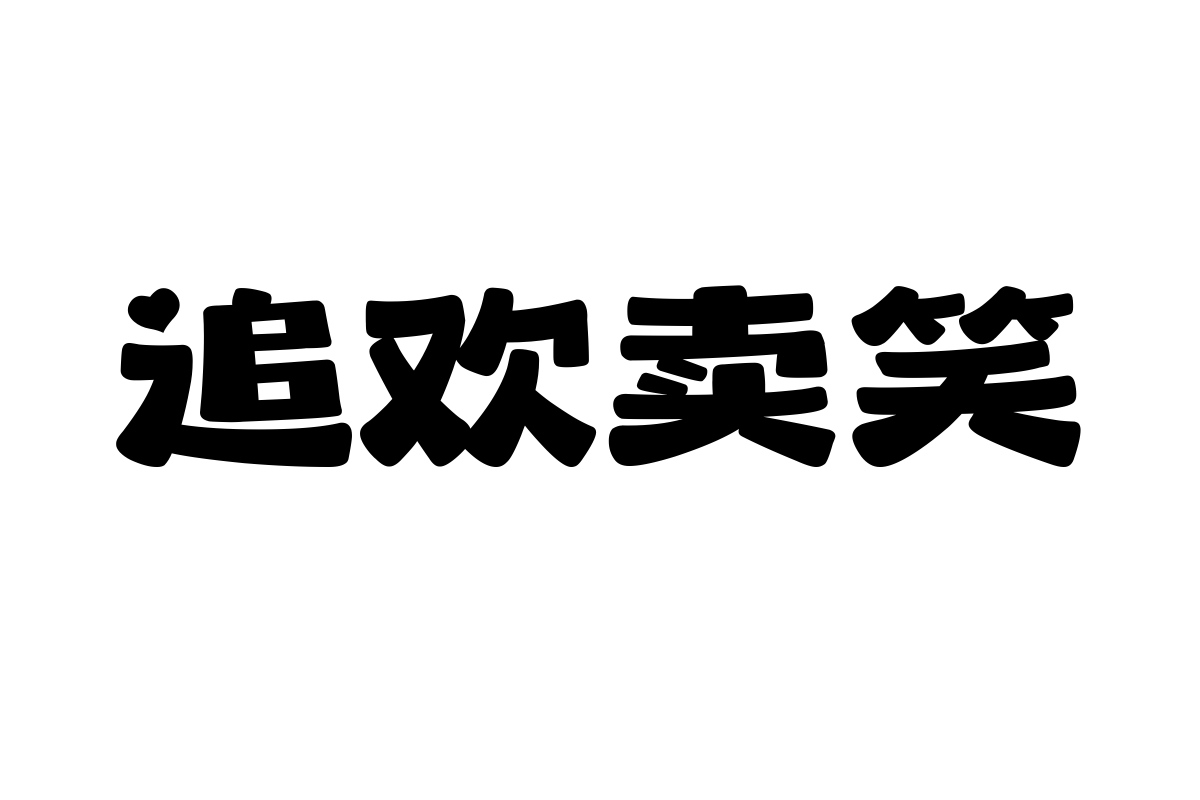
上首心愿体是一种中文字体,由上海首善文化传媒有限公司开发。这种字体具有独特的设计和风格,被广泛应用于各种设计项目中,如广告、海报、网站等。
上首心愿体的设计风格独特,线条流畅,字形饱满,给人一种温馨而亲切的感觉。它的笔画粗细适中,既有力度又不失优雅,适合用于表现情感和传递信息。此外,上首心愿体还具有一定的艺术感,能够吸引人们的注意力,提升设计的美感。
总的来说,上首心愿体是一种非常实用的中文字体,适用于各种需要表达情感和文化内涵的设计项目。